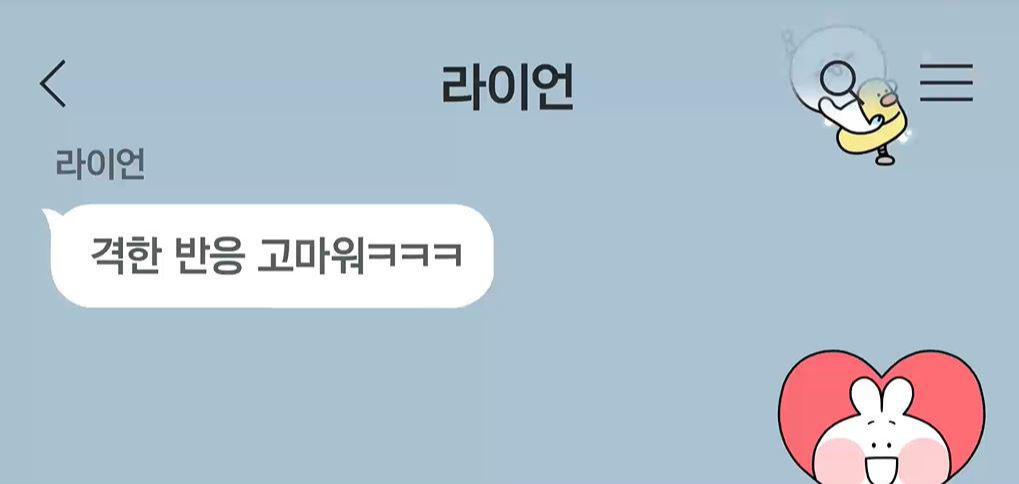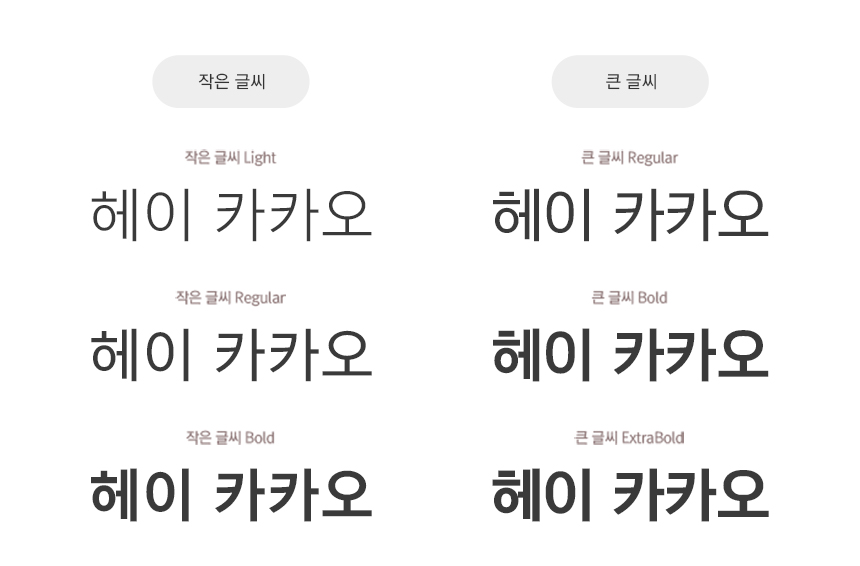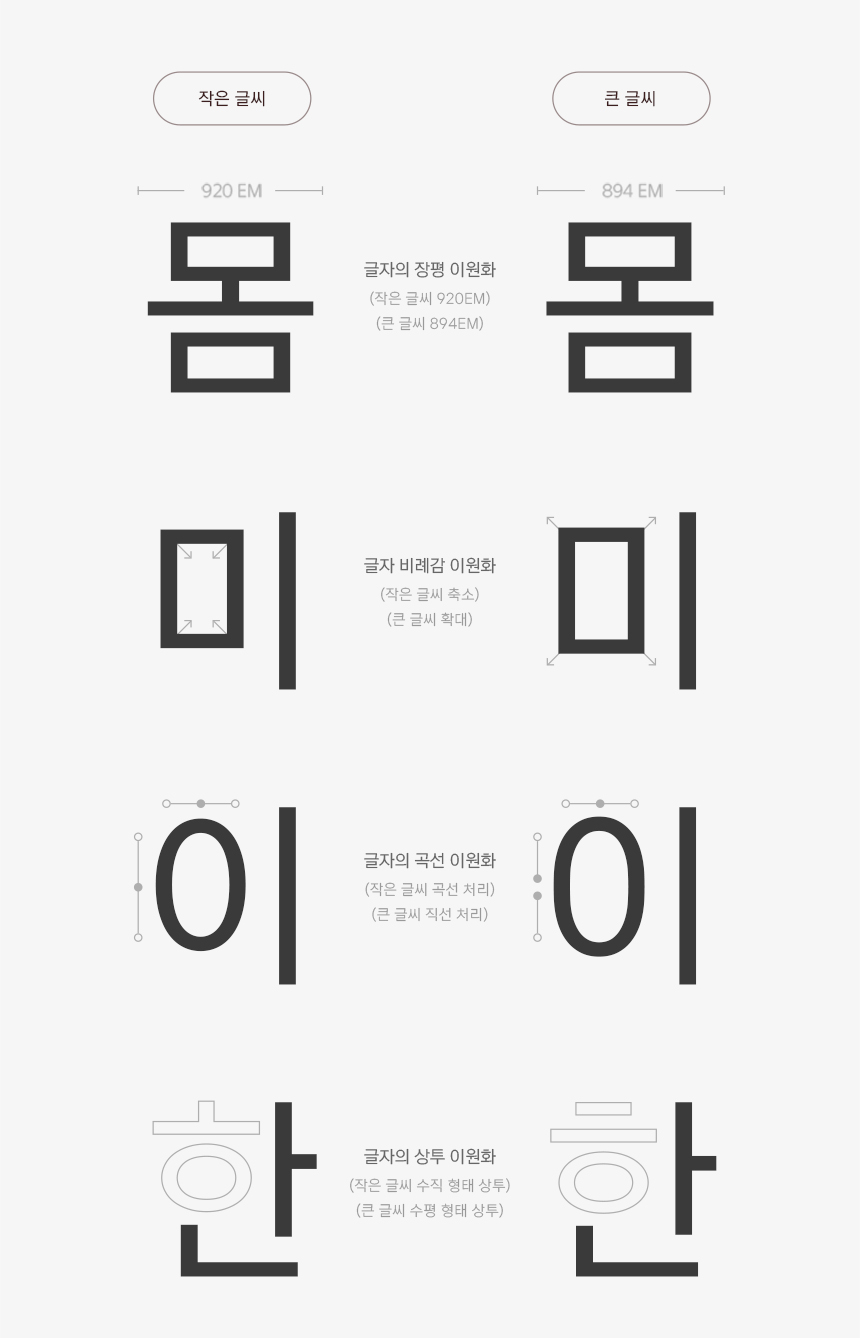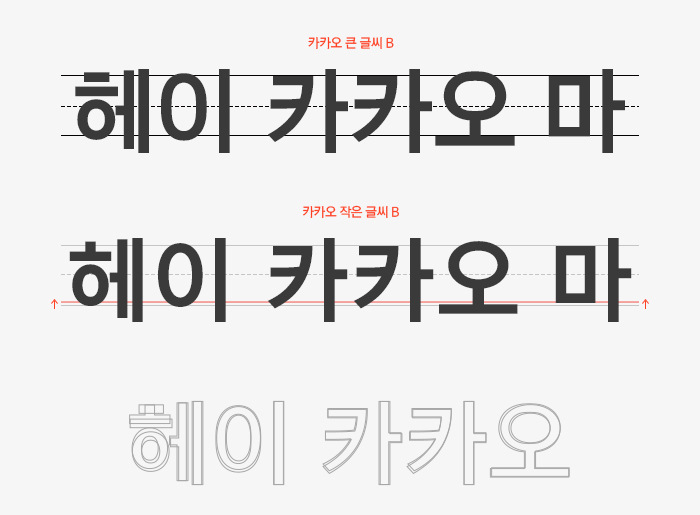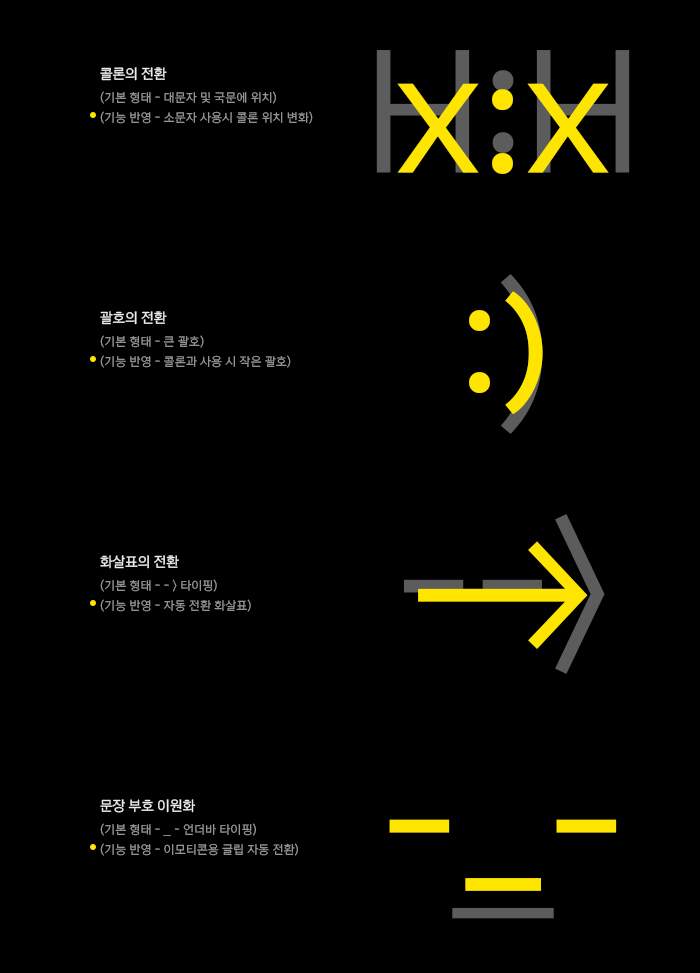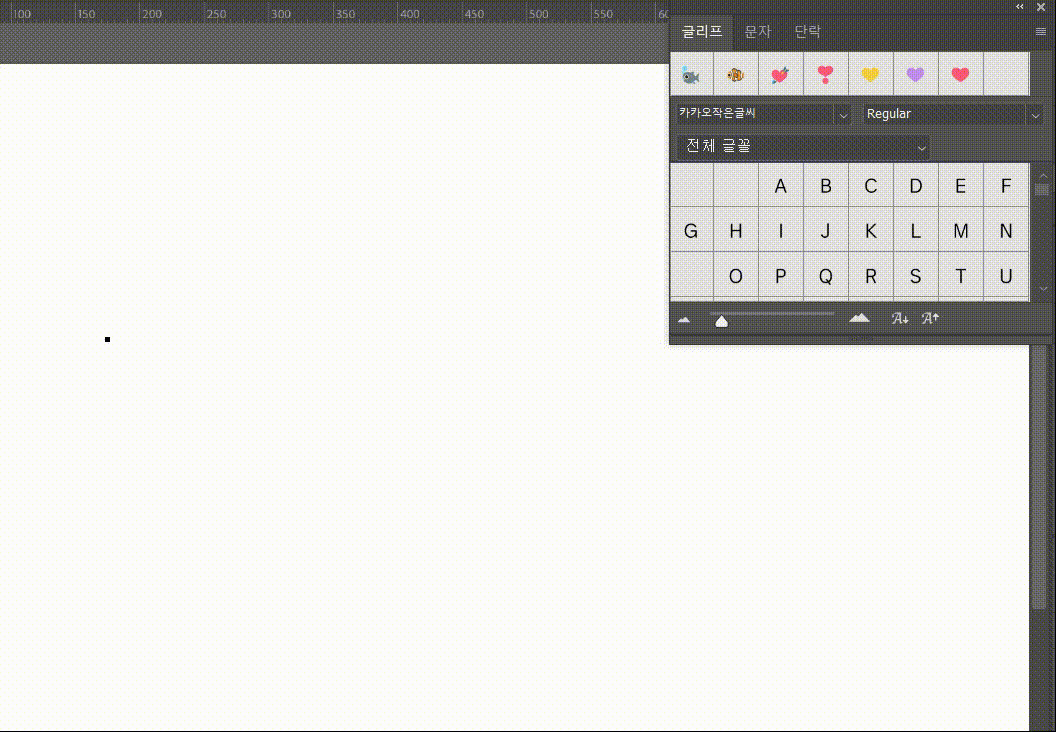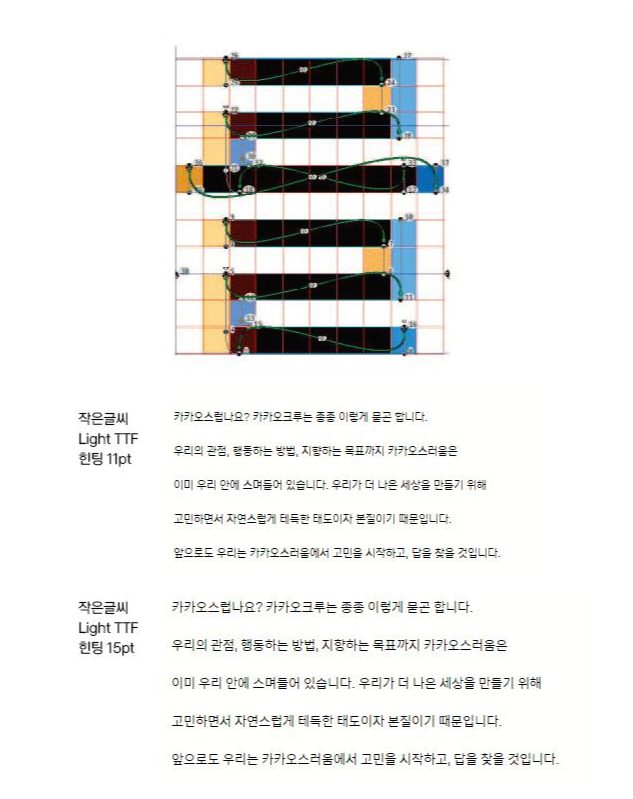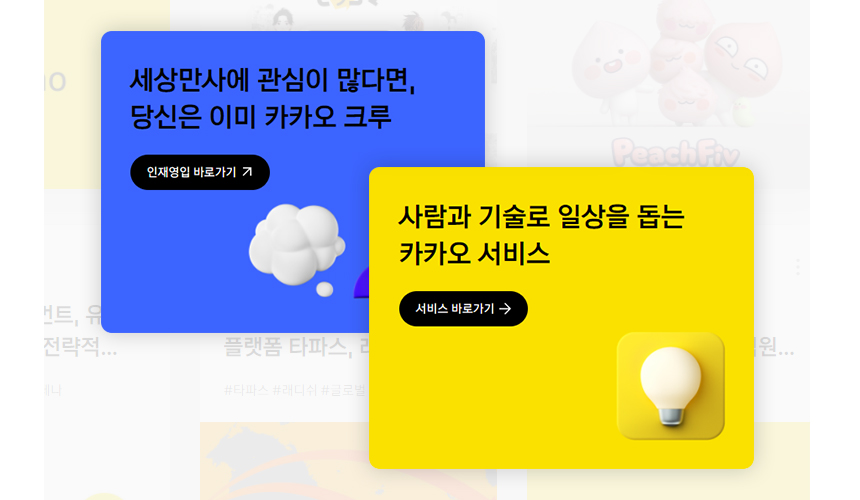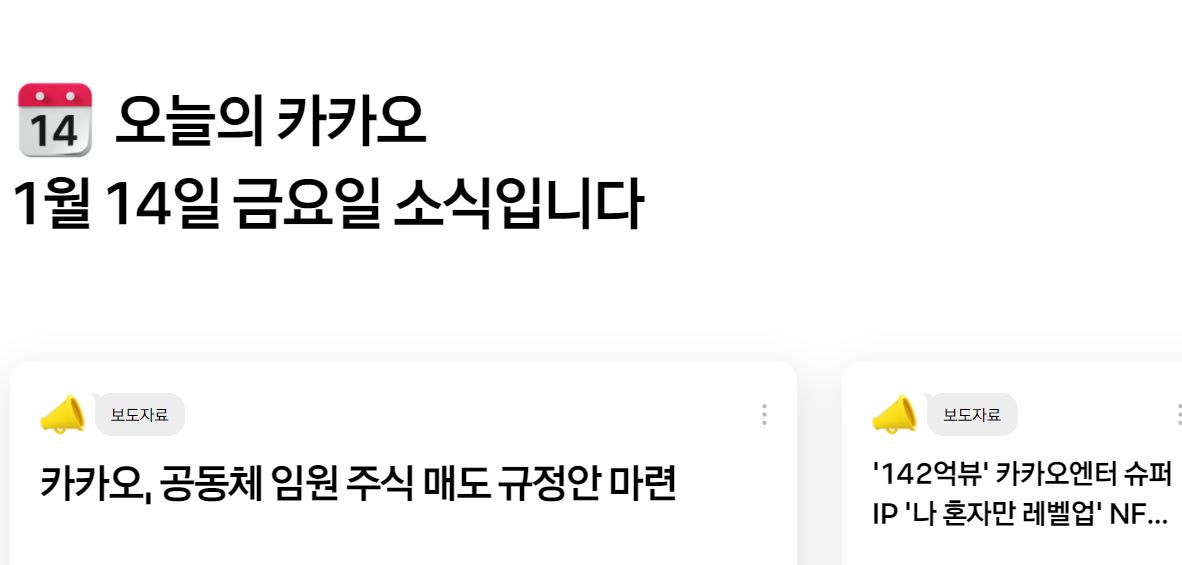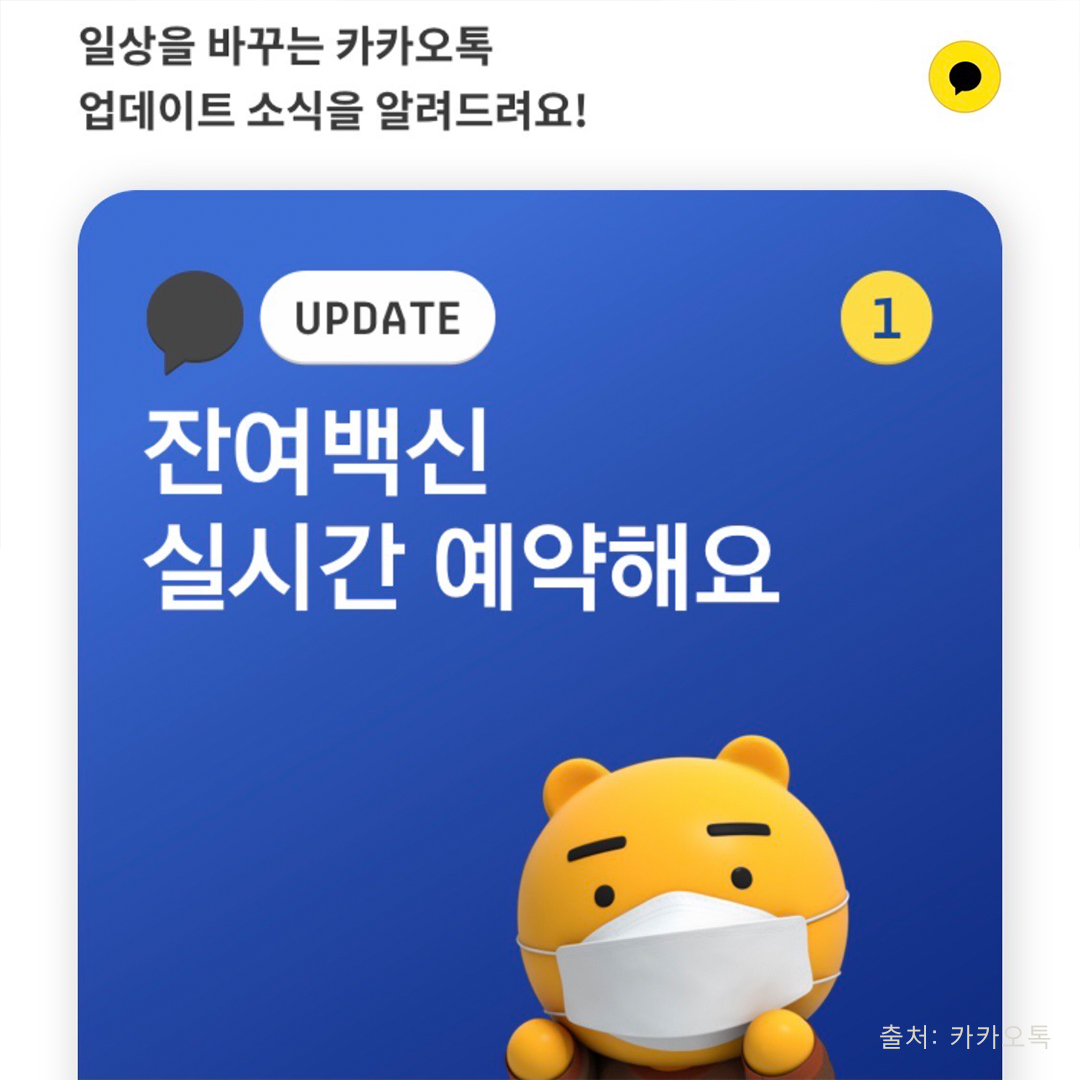
안녕하세요. 오늘은 대한민국 글로벌 기업 카카오의 전용서체 「Kakao」작은 글씨, 큰 글씨를 소개해 드립니다. 폰트릭스에서 제작한 카카오 전용서체는 모바일 및 인터넷 서비스를 제공하는 국내 굴지의 IT 기업인 만큼 사용 환경에 따라 글자가 시각적으로 가장 적절해 보이도록 '작은 글씨'와 '큰 글씨' 두 가지 버전으로 제작되었습니다. 어떤 특징이 있는지 살펴볼까요?
카카오스러운 서체, Kakao 글씨
카카오 전용서체는 디스플레이 환경에 최적화한 고딕 서체로 본문용인 작은 글씨 버전과 제목용인 큰 글씨 버전을 따로 제작하여 디스플레이에 최적화한 고딕 서체입니다. 다양한 화면에서 높은 가독성을 갖도록 고려하여 제작했으며 각 버전마다 3가지 굵기로 파생하여 활용도 측면도 고려했습니다.
글씨의 크기에 따라 적절한 글자의 장평(너비), 비례감, 이응 꼴의 곡선 처리, 상투의 형태 디자인을 각각 다르게 적용했습니다. 사용 환경에 따른 글자의 이원화 작업을 통해 화면에서의 가독성을 높였습니다.
이렇게 비교해 보면 그 차이를 좀 더 확연히 느끼실 수 있는데요. 본문용으로 제작된 작은 글씨는 본문에 더 최적화한 골격과 글줄을 적용하여 디자인된 것을 볼 수 있습니다.
기업 특성에 맞는 서체 개발
카카오 전용서체인 만큼 이모티콘 사용을 용이하게 하기 위해 특별히 OpenType Feature 기능을 추가했습니다. 이모티콘이나 심볼로 자주 사용하는 콜론이나 괄호, 문장 부호 등에 디테일한 변화를 적용함으로써 사용 환경에 따라 편리하게, 보다 자연스럽게 사용할 수 있도록 했습니다.
또한 웹폰트로 쓰이거나 작은 글씨로 쓰였을 때 좀 더 깔끔하게 보이고, 획이 많은 글자에서 뭉침 해소 등을 통해 가독성을 높이는 일환으로 힌팅 작업을 진행했습니다. 이 작업을 통해 획의 끊어짐이나 일정치 않은 굵기, 불분명한 윤곽선 등의 문제를 보완할 수 있습니다.
힌팅(Hinting)
글자의 크기가 변경될 때 왜곡 없이 출력 결과를 얻게 되는 과정. 보통 글자 크기가 작을수록 화면에서 글자가 깨끗하게 보이지 않는 문제가 생기는데 이를 해결하기 위한 작업입니다.
카카오 글씨의 활용
현재 카카오 전용서체는 공식 홈페이지, 카카오톡, 이모티콘샵, 유튜브 등 다양한 디스플레이 환경에서 사용되고 있습니다. 작은 글씨와 큰 글씨 모두 뛰어난 가독성으로 작은 폰 화면으로 텍스트를 읽거나 글자를 접하는 경우에도 편안하게 읽을 수 있습니다.
카카오톡 내 여러 서비스에서도 만나볼 수 있었는데요, 카카오구독ON과 같이 정보성 짙은 콘텐츠의 경우 긴 글이 많기 때문에 본문에는 작은 글씨, 제목에는 큰 글씨를 사용해서 텍스트가 눈에 쉽게 들어오는 것을 확인할 수 있습니다.
고딕체를 기반으로 한 글씨체는 우리 눈에 기본적으로 익숙한 편안함과 안정감을 줍니다. 더불어 최적의 비율로 제작한 서체의 완성도와 가독성으로 카카오의 여러 콘텐츠에서 높은 활용도를 보이고 있습니다. 사용성에 큰 비중을 두고 오랜 기간 개발하고 제작한 만큼 앞으로의 활용도 기대되는 부분입니다.
카카오의 기업 니즈에 적합한 서체로 높은 활용도를 가진 전용서체를 개발했습니다. 한글 11,172자 / 영문 94자 / 심볼 986자로 2가지 버전, 총 6종의 굵기를 제작하는 긴 프로세스였기 때문에, 2년여의 기간을 착수한 끝에 2021년 개발을 완료했습니다.
카카오에 어울리는 한글 디자인 방향성, 한글과 조화로운 영문 디자인 작업과 모바일 적용 테스트까지 수많은 커뮤니케이션을 통해 완성된 전용서체라 더욱 의미 있던 사례입니다. 폰트릭스의 숙련된 기술과 기업에 대한 높은 이해도로 제작하는 기업전용서체는 브랜드 이미지를 구축하는 밑거름이 될 수 있습니다.